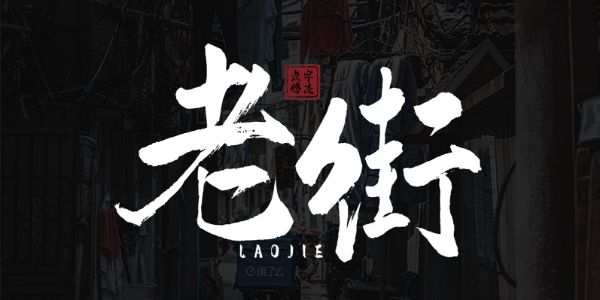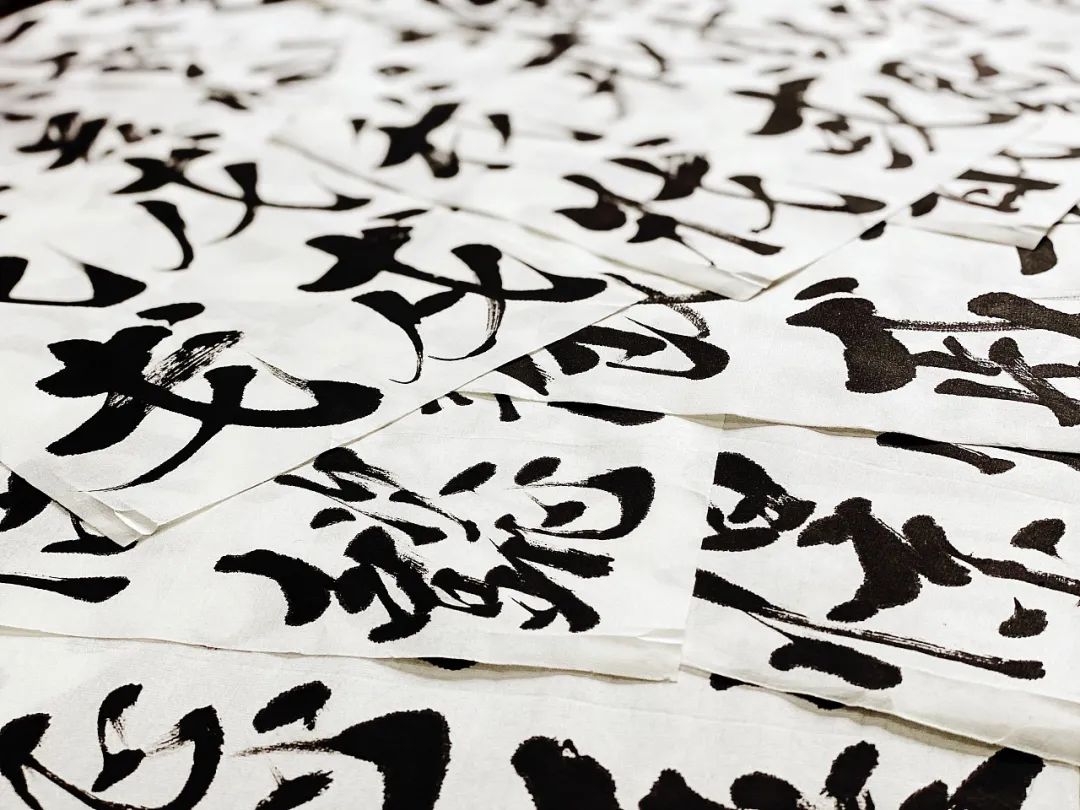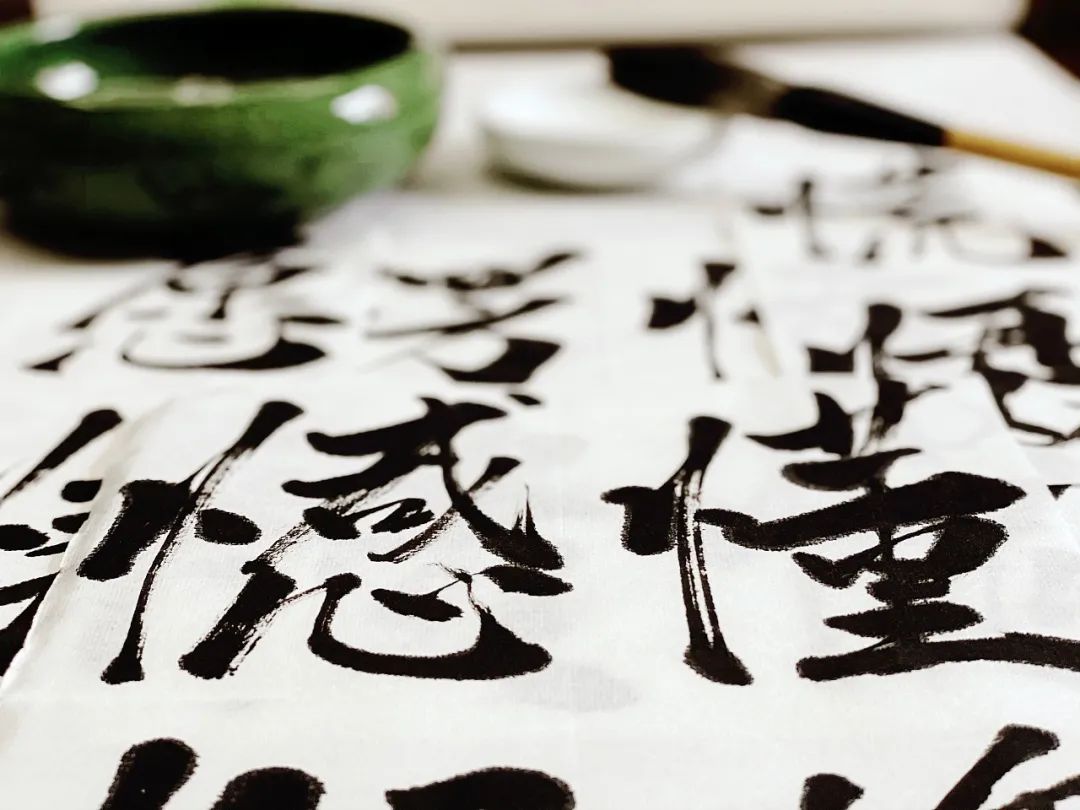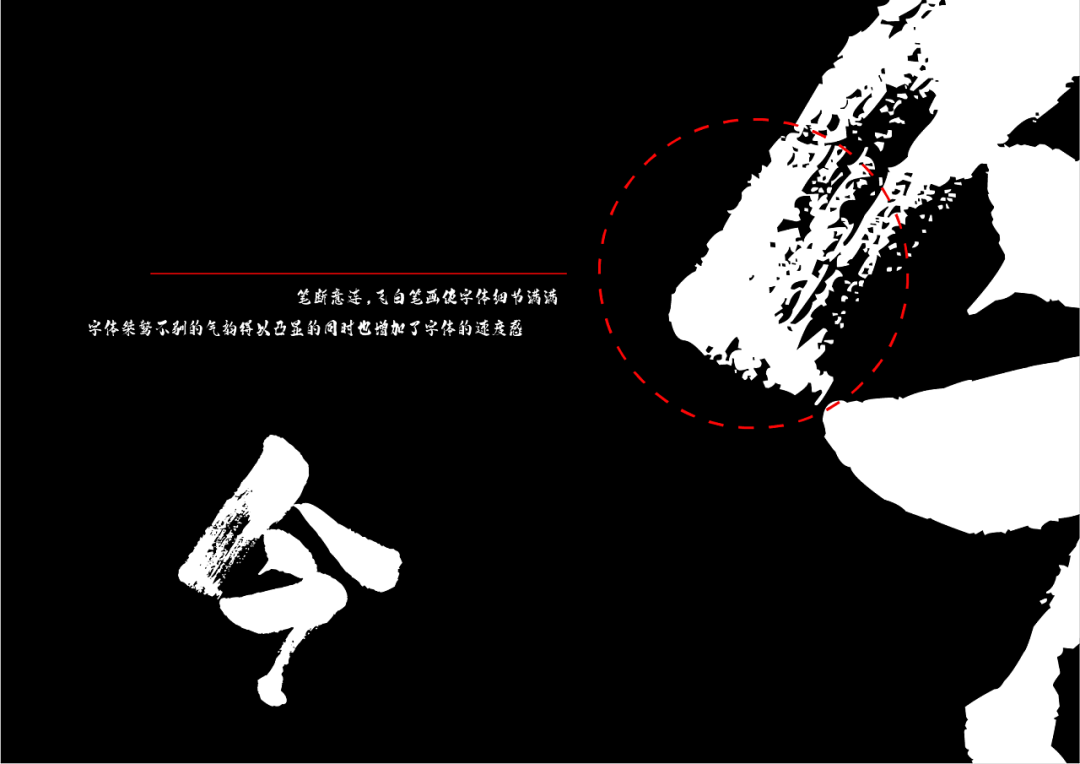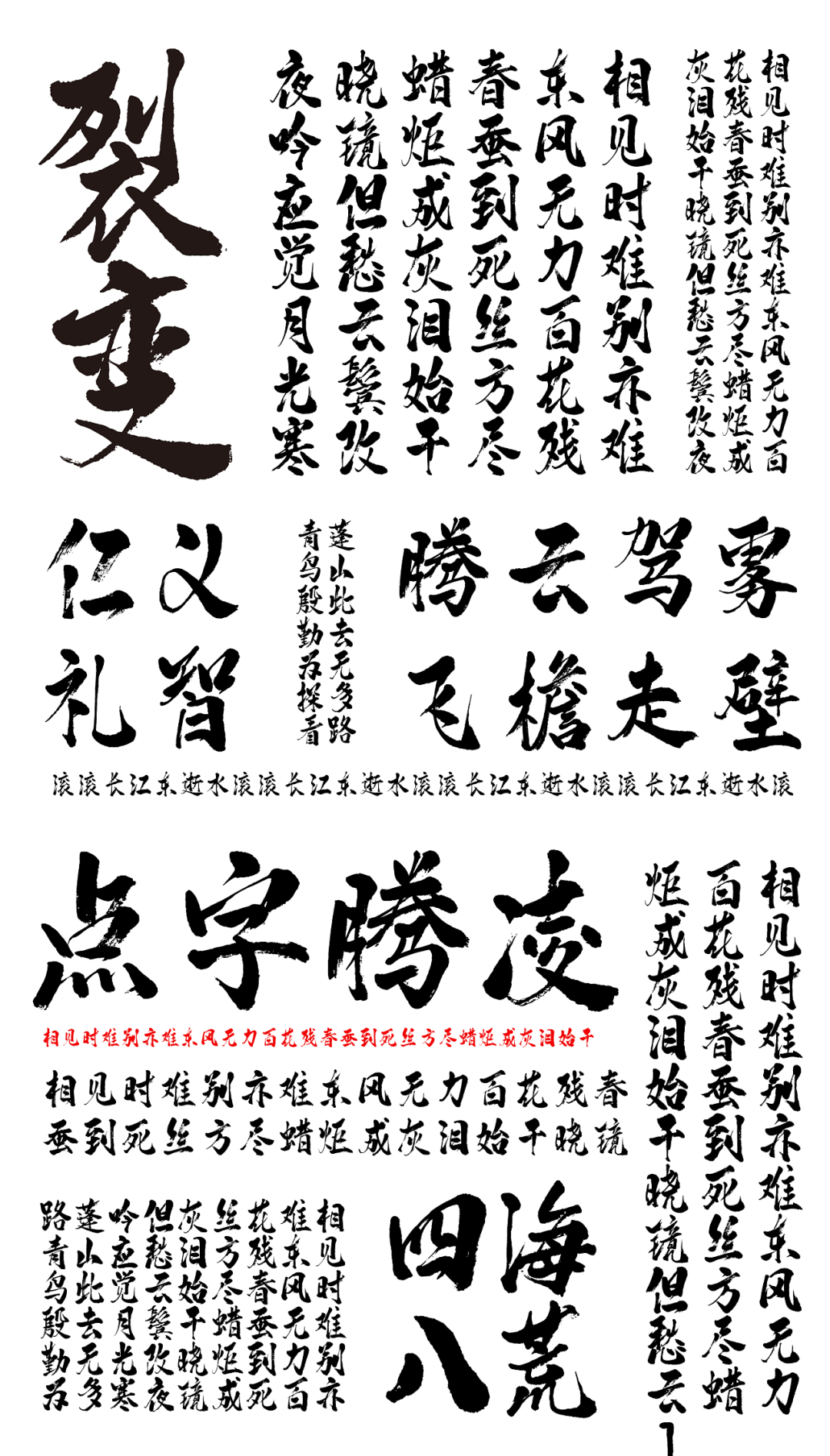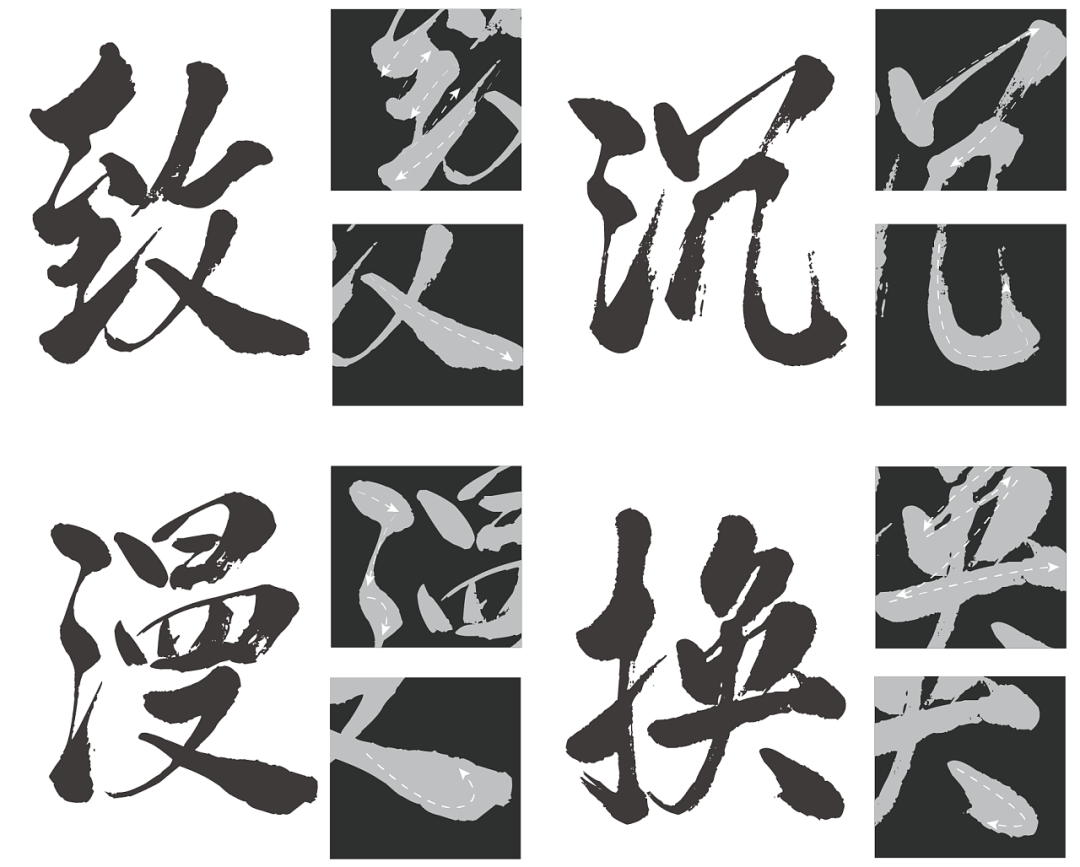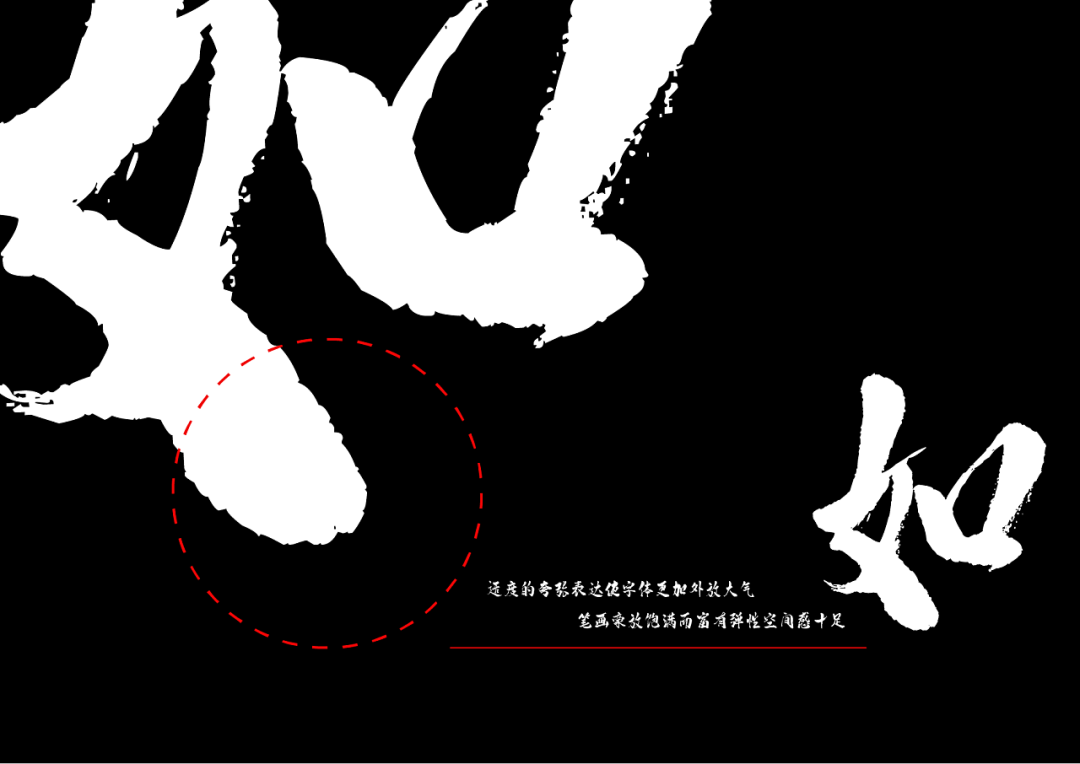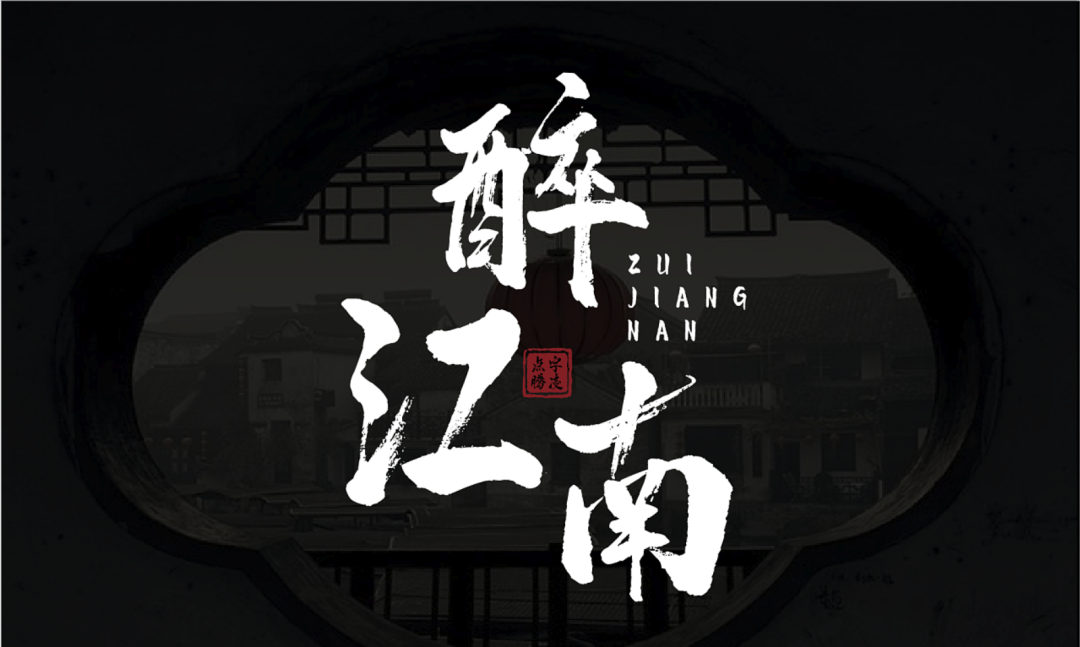
那今天就给你透露一款仅在字由客户端+会员专享的新字,点字腾凌体!
听到这个名字,柚子脑海中第一时间就浮现大圣翻跟头(腾)和段誉走凌波微步(凌)的画面,看看之后能不能做在视频里(关注字由视频号),哈哈哈!
不过话说回来,看到这个字稿,你就应该猜到,设计师背后手写的不易~
再看看笔画细节,有饱满、飞白,一气呵成。
整体排版,能看到字里行间的“侠”气!
用做标题设计,有一种油然而生的历史感。
用在海报中,一秒占据视觉C位!